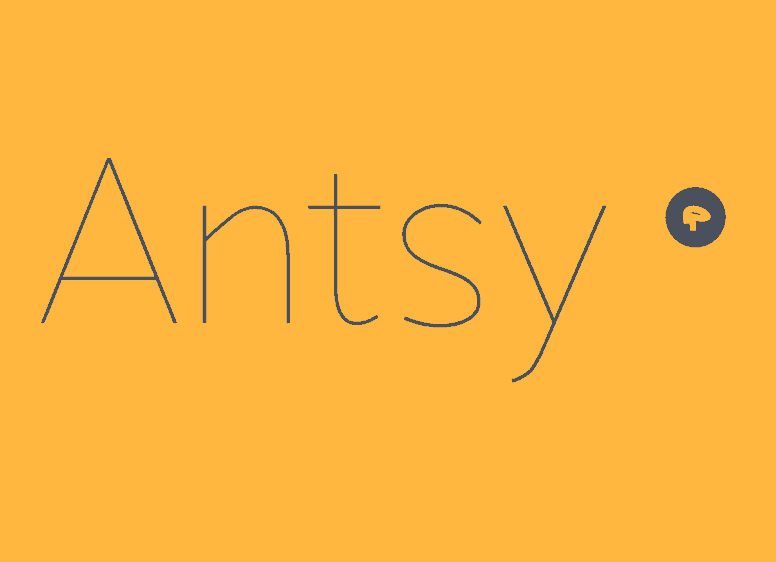
A Antsy Font Family é uma nova atração para designers digitais apaixonados pelo estilo moderno e versátil do sans-serif. Desenhada por Byeongsu Kim, um talentoso designer sul-coreano, esta família de fonts incorpora influências únicas da escrita pessoal do autor. O resultado é um tipo humanístico que se destaca não apenas pela sua elegância gráfica, mas também pelo seu uso criativo das ligaturas e dos espaçamentos ricos. Com uma densidade impressionante em termos de calibre e espaciamento entre caracteres, a Antsy Font Family vai além da simples funcionalidade do tipo sans-serif. Suas características também permitem usá-la em diversos contextos, desde o design gráfico até elementos de marca ou headlines digitais. Além disso, seu formato display oferece um toque extra de personalização e impacto visual ao seu projeto, tornando-a uma escolha perfeita para designers atemporais que valorizam tanto a simplicidade quanto a expressividade. A Antsy Font Family é mais do que apenas mais uma opção no seu arsenal de tipos digitais. É um complemento versátil e divertido ao seu trabalho, desafiando-o a explorar diferentes direções com o poder e a liberdade da fonte sem deixar para trás qualquer elemento essencial ou criativo. A partir de hoje, pode ser tempo de experimentar uma nova maneira de combinar design e estilo.